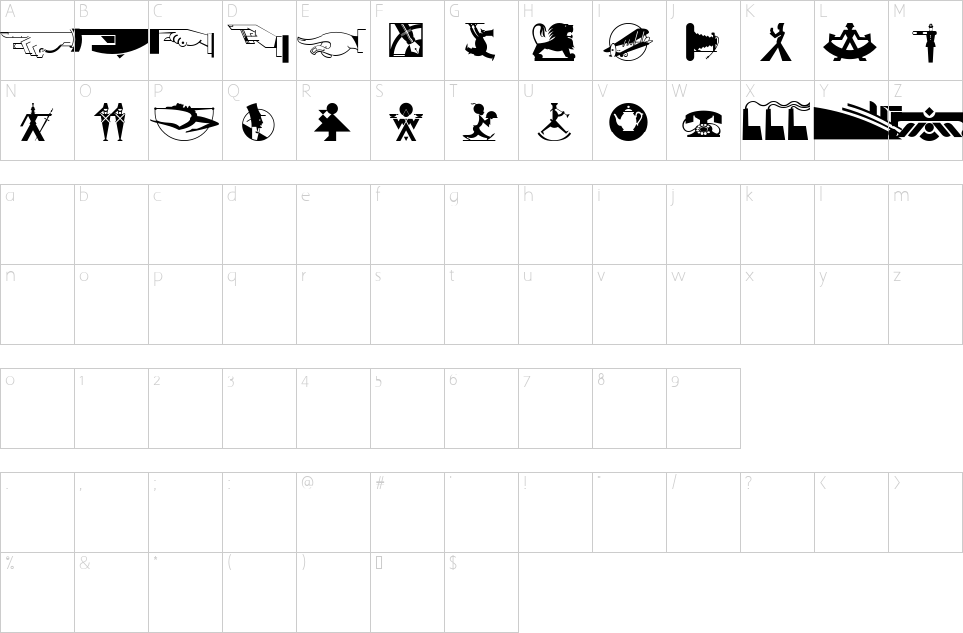
DecoDingbats Font
Descubra a DecoDingbats Font, uma fonte original e única para Windows e Mac, criada por Nicks Fonts e baixada mais de 5 mil vezes pela comunidade global. Esta fonte decora seus documentos com um toque especial, combinando formas icônicas e detalhes sofisticados em um design que se destaca da multidão. Seja para o seu próximo projeto gráfico ou newsletter, adote a DecoDingbats Font para trazer vida e personalidade à sua escrita digital. Compostas de maneira criativa, essas letras ornamentais não apenas destacam-se, mas também se integram naturalmente às suas mensagens. Descubra por si mesmo o poder transformador da DecoDingbats Font e veja como ela pode revolucionar a aparência de seu trabalho gráfico.
Mapa de caracteres da fonte DecoDingbats Font